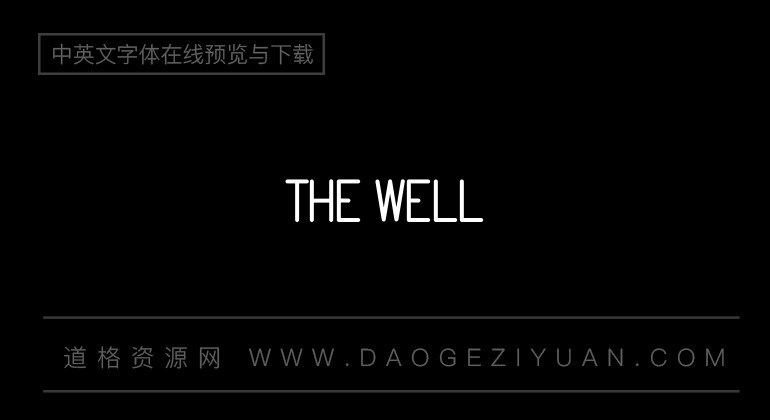
The Well 是一款简洁、现代的字体,由荷兰设计师 Frank Hemmekam 创作。它拥有宽松的字形,结合了坚实的结构,具有优雅、时尚的外观。The Well 字体以细节为重点,给人以非常好的视觉体验,可以用于各种品牌、商业、媒体和其他应用场景。它的构成元素有助于增强文本的可读性,也可用于设计标题和标签,为设计师提供更多的创意空间。内容介绍
The well是一款非常不错的手写艺术字体,具有很好的视觉感,适合于文化类的宣传设计、商业类品牌的广告和产品包装设计以及个性化文字排版等较多场景。